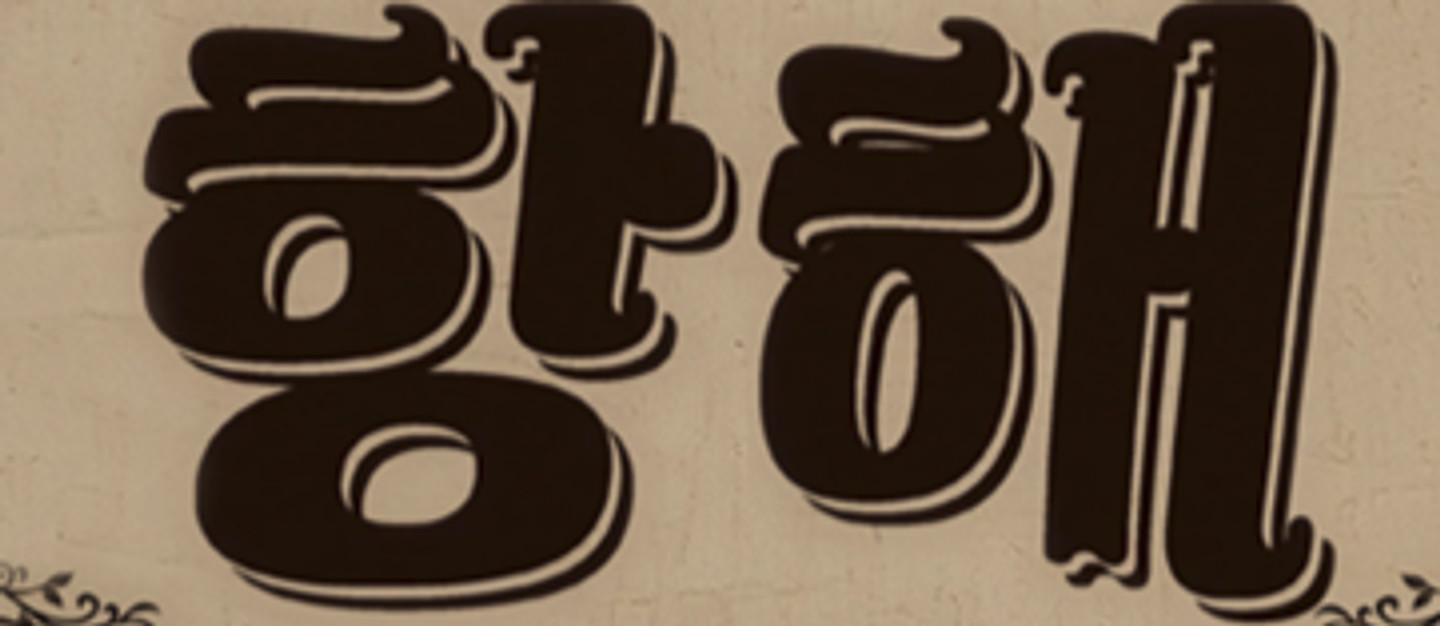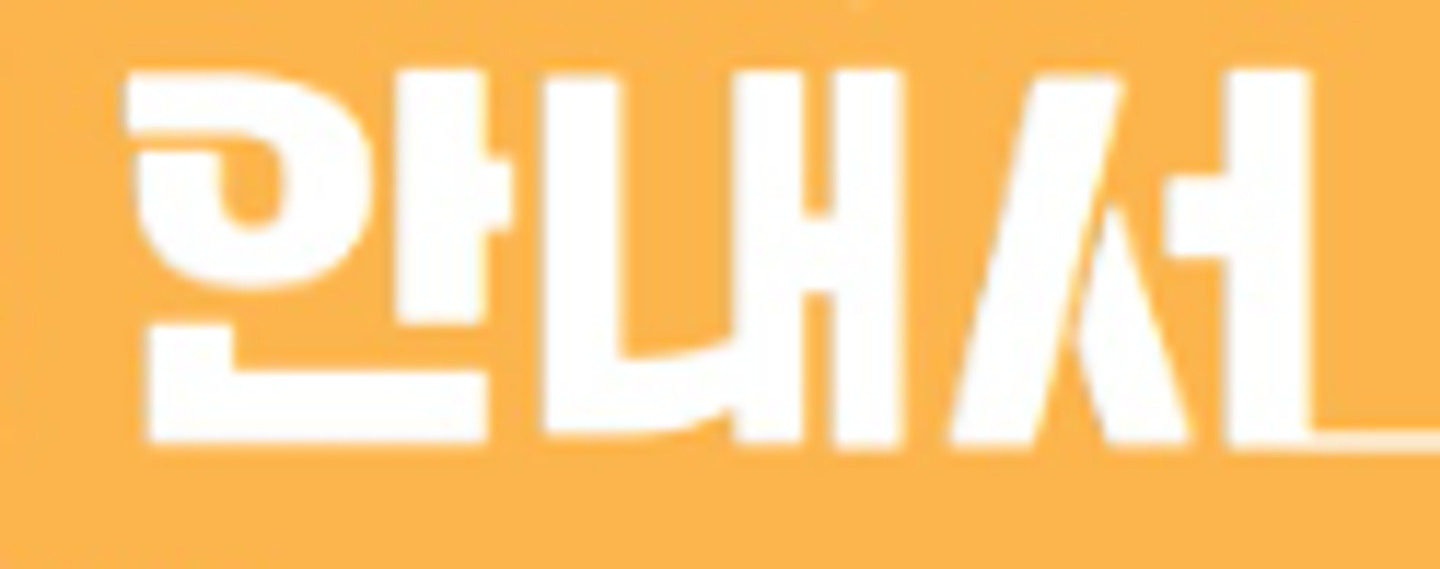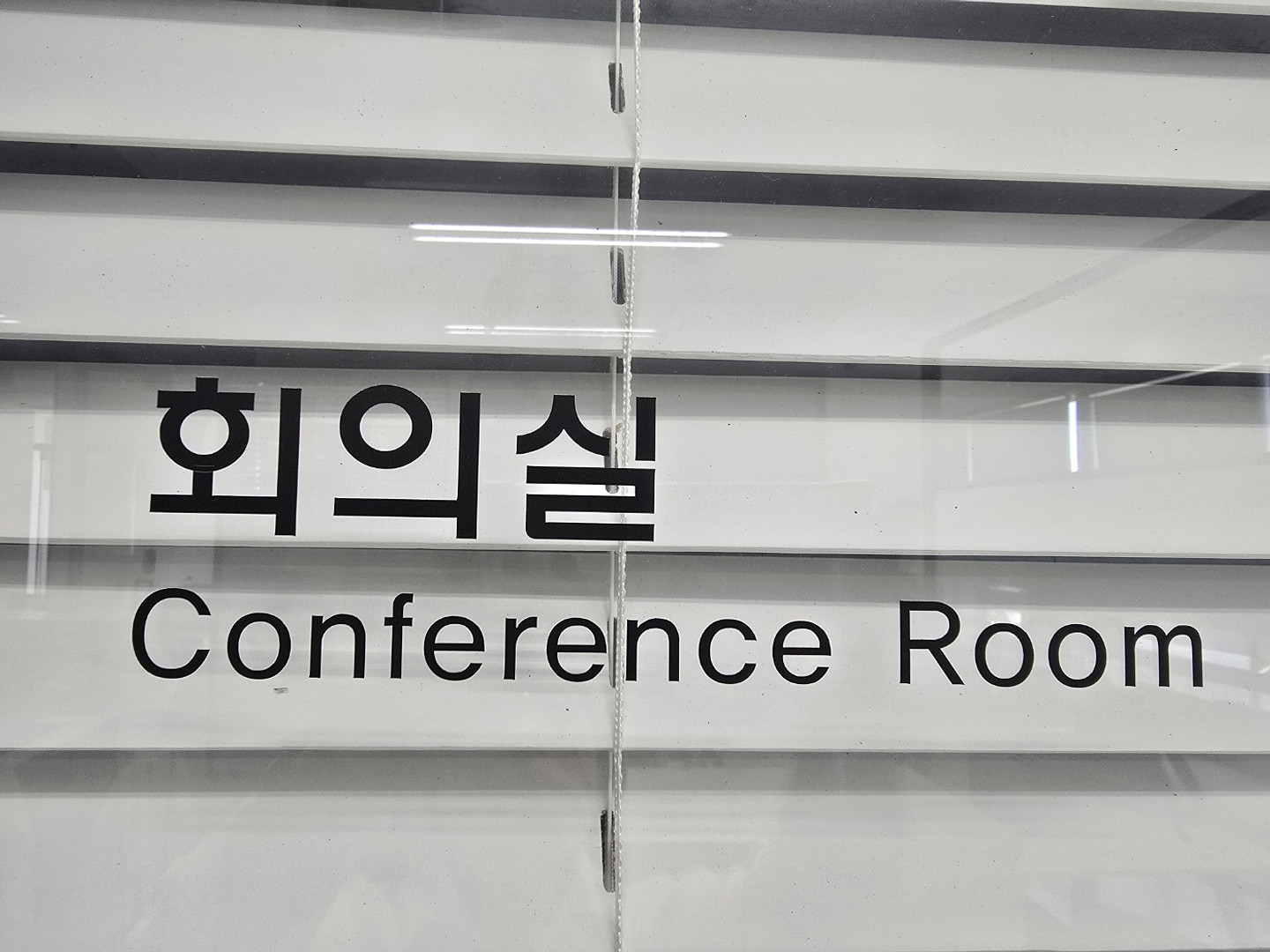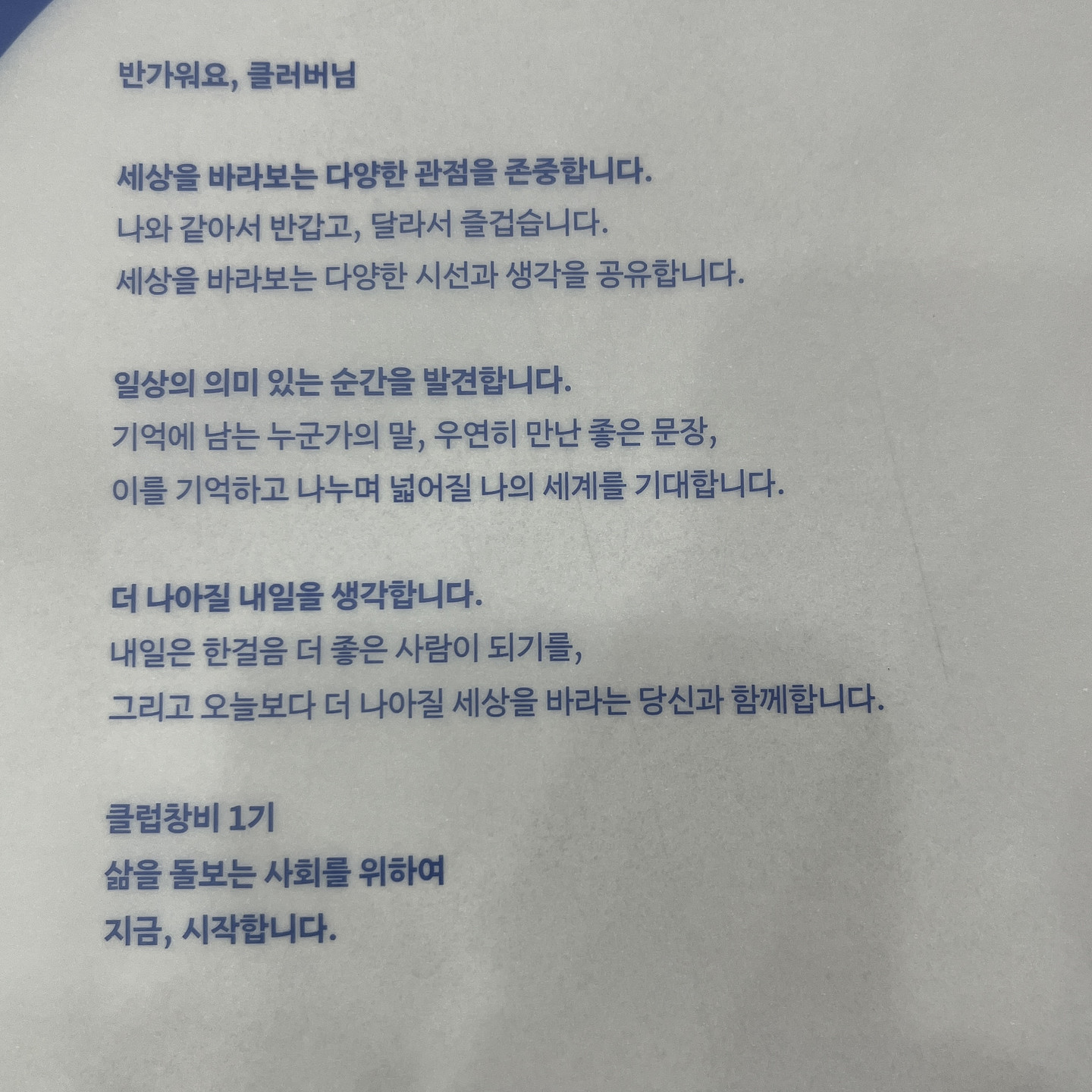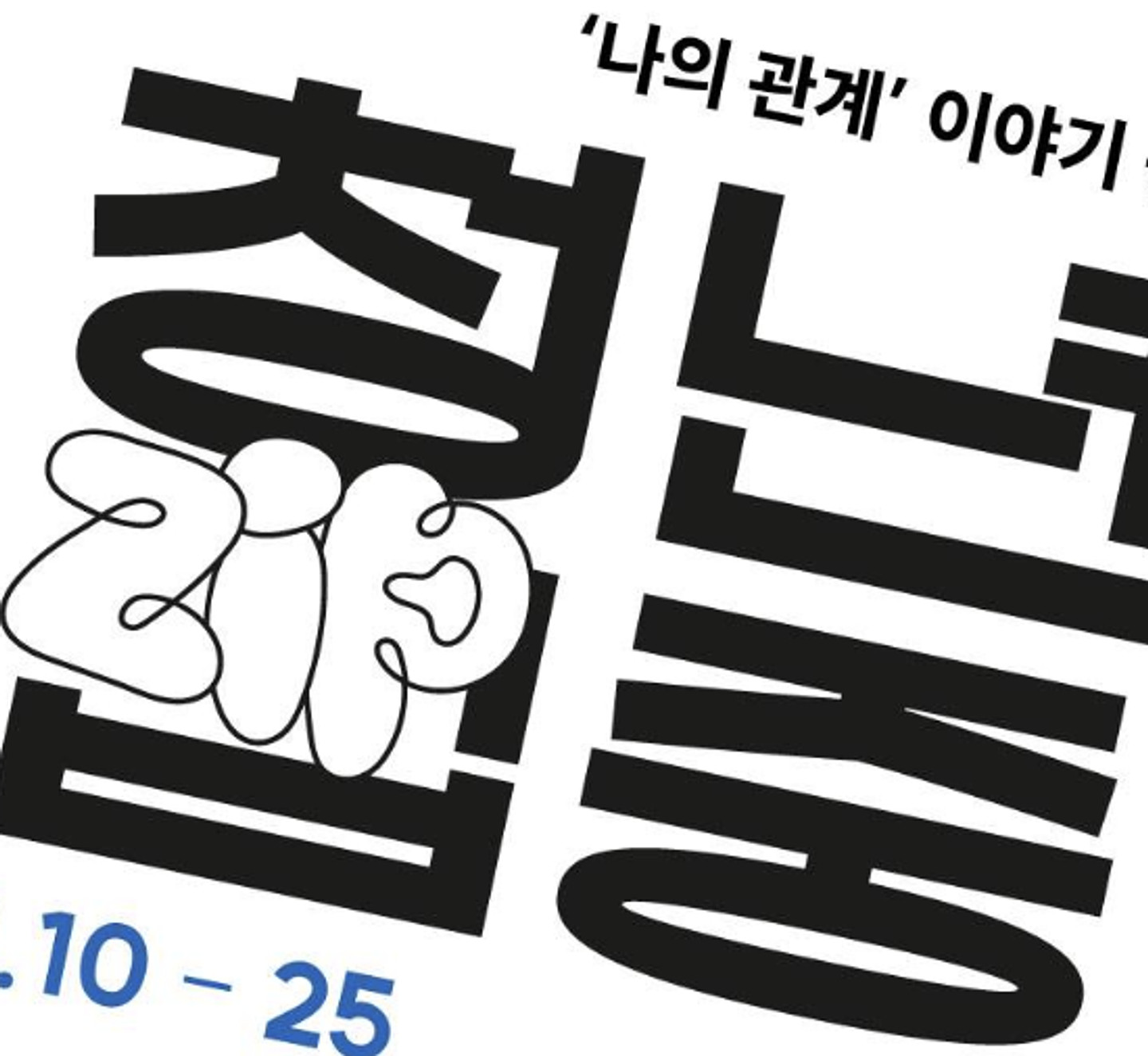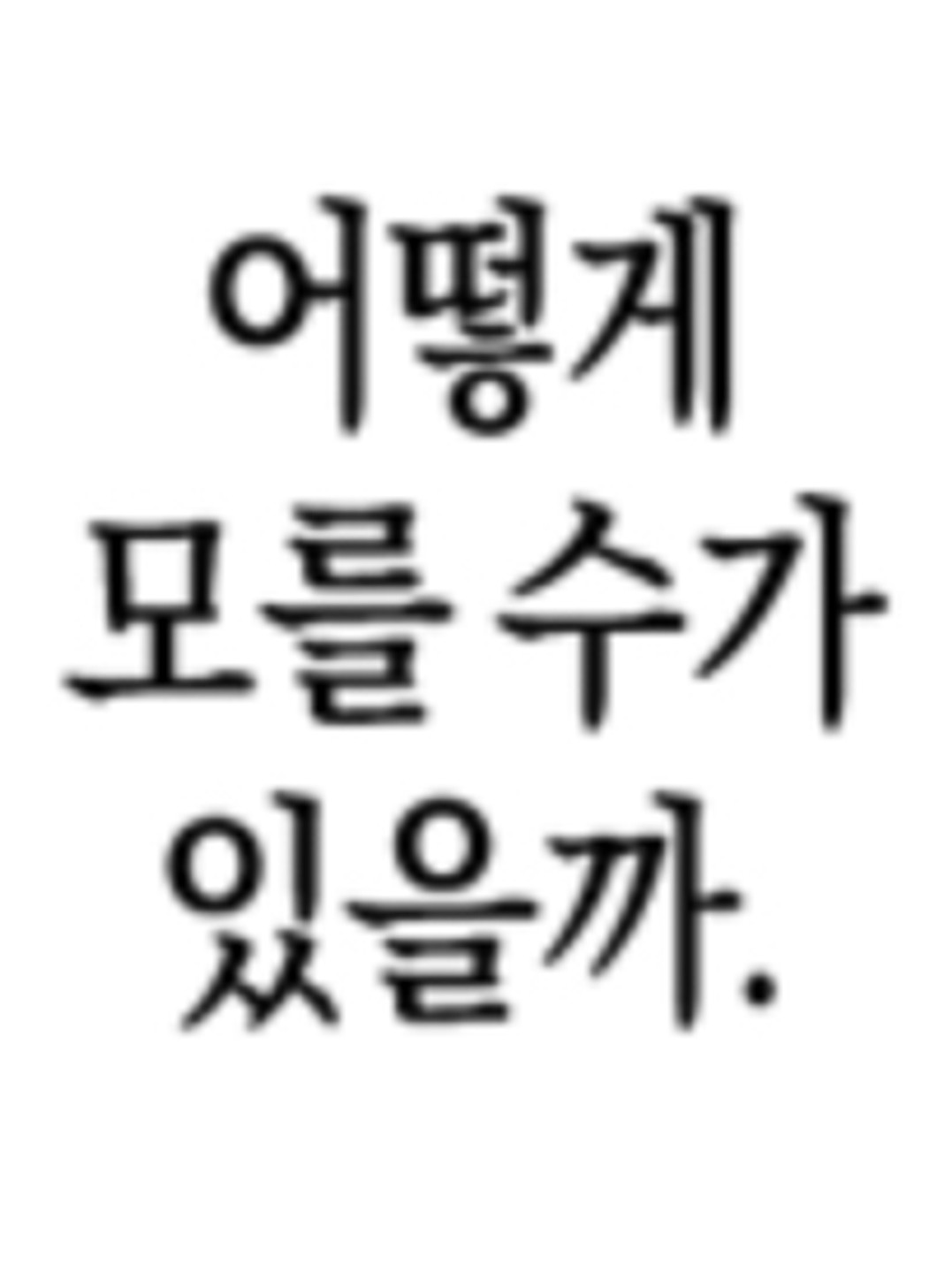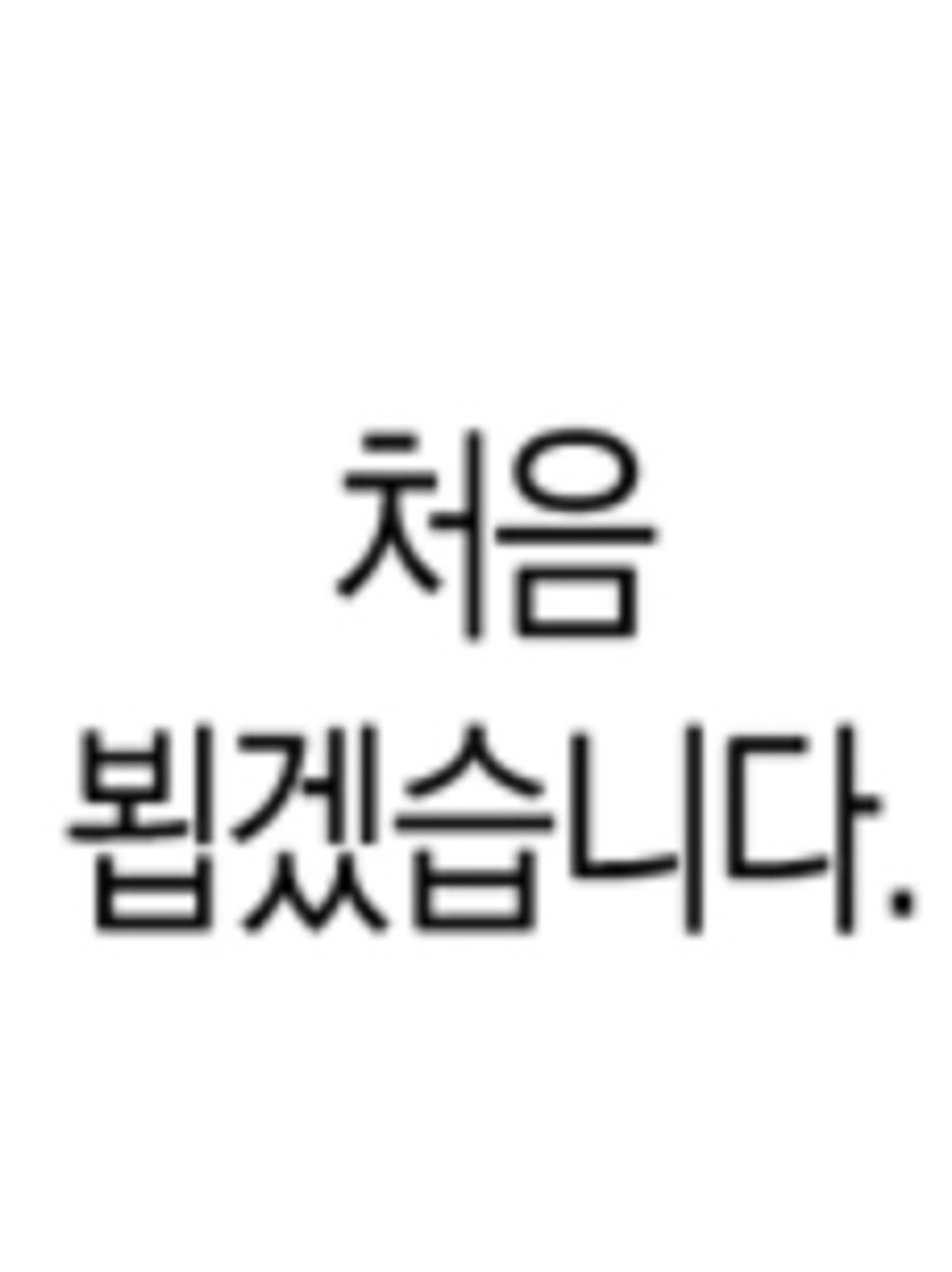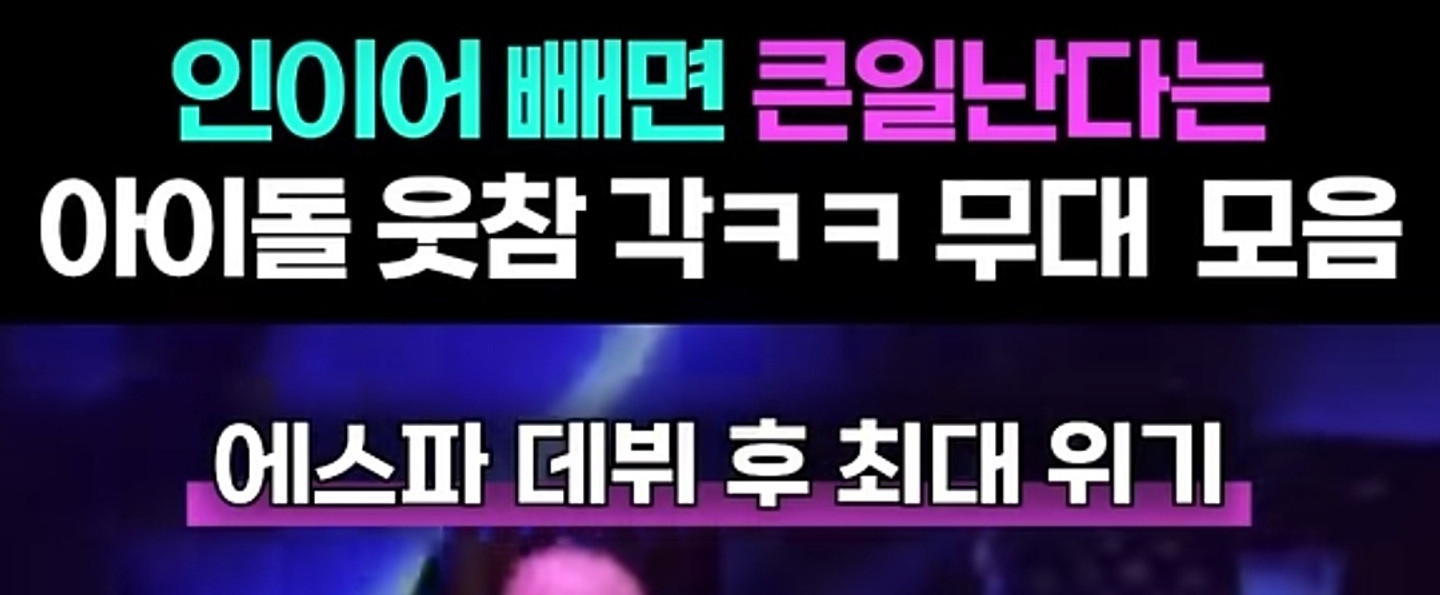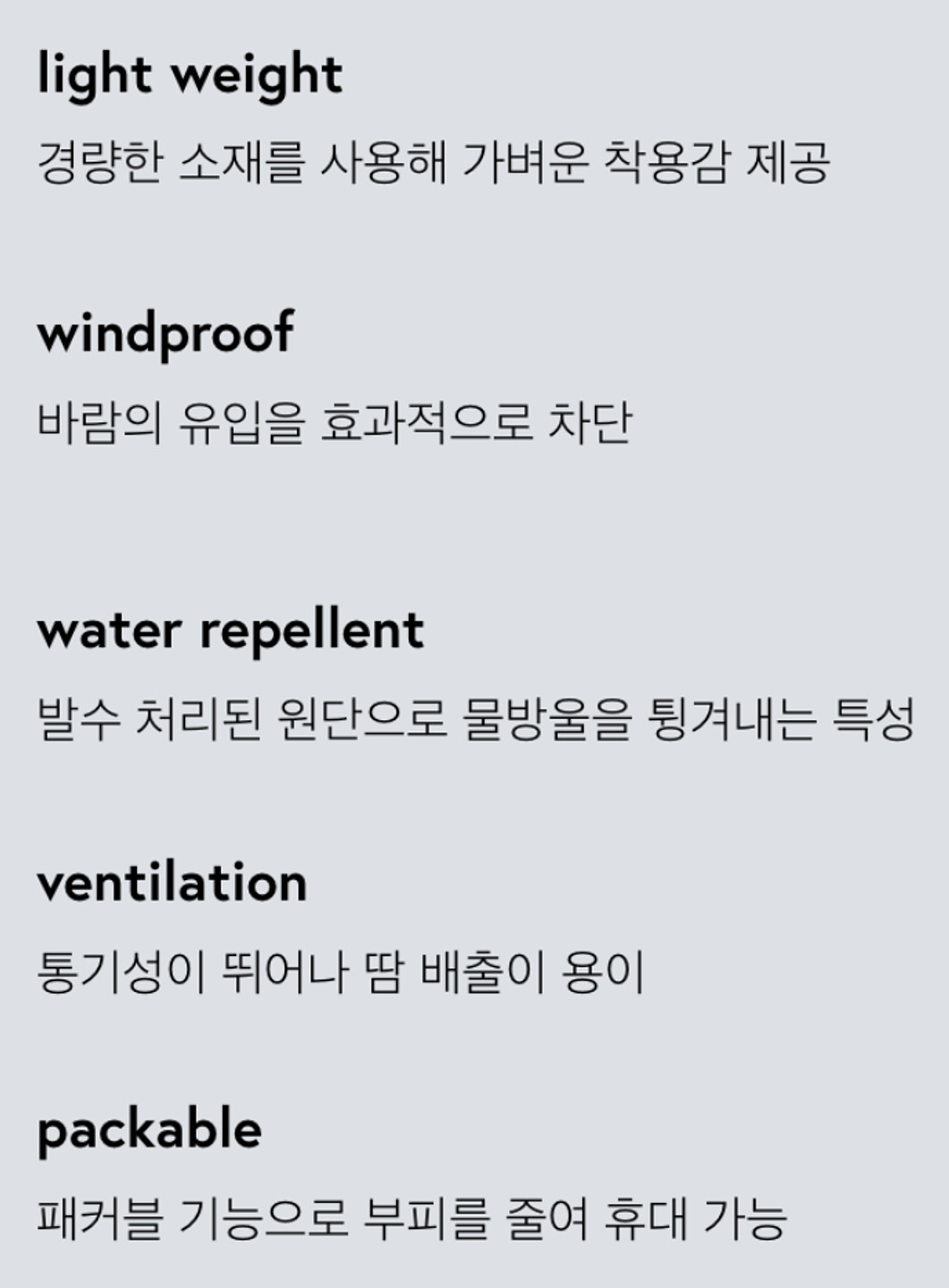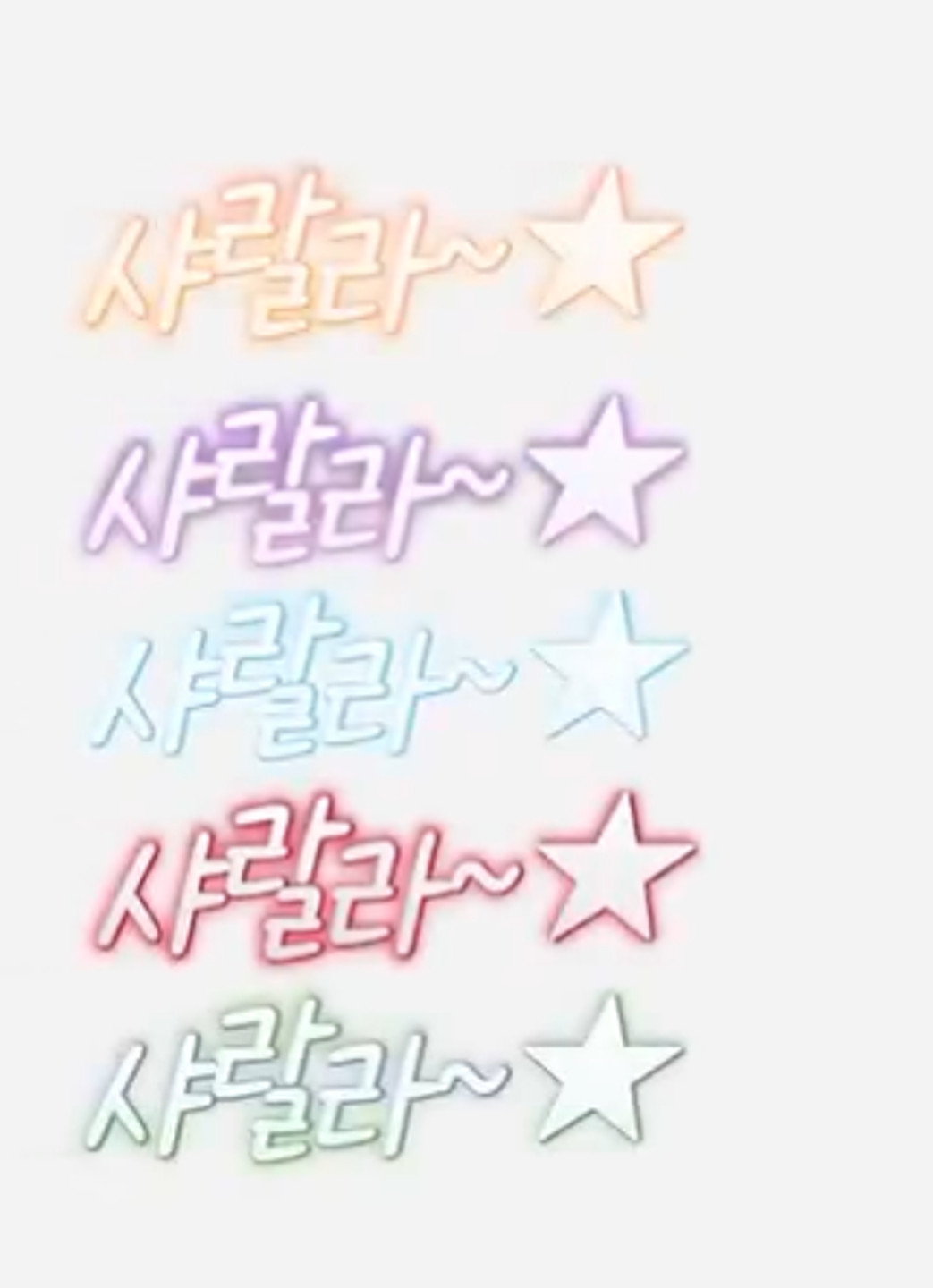
이렇게 길고 세리프 있는 폰트체 있을까요,,
폰트 명을 잊어버렸어요
이거 무슨 폰트인지 알 수 있나요?
폰트뭘까요?
폰트 뭘까요
폰트 뭘까영
이거ㅕ 기본 굴림체인가요?
붓으로 쓴 듯한 폰트인거 같아요
혹시 이 폰트 뭔지 알 수 있을까용 ㅜㅜ??!!
이 폰트는 무슨 폰트인가요?
폰트명이 어떻게 될까요?
굴림체 종류인거 같긴 한데.. 똑같은건 못 찾겠네요ㅠㅠ 이 폰트 아시는 분!! 알려 주세요ㅠㅠ
이거 무슨 폰트인지 알고싶읍니다
유튜브 보다가 이 폰트 너무 궁금합니당
몰라
이거 폰트 너무너무 찾고싶은데 폰트 이름 뭔지 알 수 있을까요??
땨 꾛 같은 외계어 지원되있는 폰트 궁금합니다. 특히 카톡 오타 날때마다 폰트 바뀌는게 신경쓰여서
이폰트 고수님들 아려 주세요 DIN 종류는 아닌거 같아서요
안녕하세요 고수님들, 동그라미친 부분에 있는 폰트는 무슨폰트일까요??
디즈니 모두의 리그 한글 폰트가 뭔지 궁금합니다.
네이버 스토어 폰트 뭔가요>?
권진아 꽃말 콘서트 영어 폰트 뭔지 궁금합니다.
여기쓰인 폰트가 무엇인가요? 그리고 이 폰트 처럼 폰트 자체에 수크래치된 것 같은 음영이나 브러쉬효과 같은게 들어간 폰트를 찾고 싶으면 무슨 폰트 카테고리를 검색해야 하나요? 이럼 유형의 폰트를 무슨 폰트라고 하는지 알려주세요^^
이 도장에 사용된 글씨체 뭘까요?ㅠㅠ
이 폰트 몰까요ㅠㅠ?
영어 한글 둘다 알려주세요 궁금합니다
무슨 폰트인가요ㅠㅠ
추성훈 썸네일 폰트 뭔지 아시는 분 있으신가요..?ㅠㅠ
지나가다가 본 캡쳐에 있는 폰트인데 도저히 뭔지 모르겠어요ㅠㅠ 이미지로 찾는 것도 해봤고 눈누에서도 일일이 넘겨가면서 봤는데 찾기가 힘드네용ㅠ 너무 제 취향이라 꼭 찾고 싶은데 도와주세요!!
혁신 숲 폰트
기존 로고 시안에 있는 글씨체인데 혹시 어떤 글씨체인지 알수있을까요?
이 서체.... 쓰고싶은데 대체 뭘까요 산돌에 검색해도 안 나오네요
이거 무슨 폰트일까요..?ㅜㅜ
이 폰트 멀까요8ㅅ8
아시는분!!
이 폰트 뭘까요... 너무 취향인데ㅜㅜ
라이즈 자컨에 나온건데 무슨 폰트일까요?
이 폰트 몇달 째 찾아다니는데 못찾겠어요,, 아시는분 제발 알려주세요 😭😭
이거 무슨 폰트일까요!!!!
폰트 이름좀 알려주세요
이거 폰트 아시는분 계실까요..??
이게 무슨 폰트일까요~??
이 폰트 아시는 분 있을까요?
요거 무슨 폰트일까요..?
유튜브 보다 뜬건데 무슨 폰트 일까여?
혹시 이 폰트 뭔지 아시는분 계실까요..??
인스타에서 보고 캡쳐한 건데 이거 글씨체 뭔지 알수 있을까요?ㅜㅜ
똑같거나 비슷한 굵은 폰트 좀 알려주세요.
배스킨라빈스 리뉴얼 한글 폰트 알려주세요
이 폰트 어떤 폰트인지 알수있을까요?
이 영어 글씨체 뭘까요>>??
어떤 폰트인지 아시는 분 계신가요?